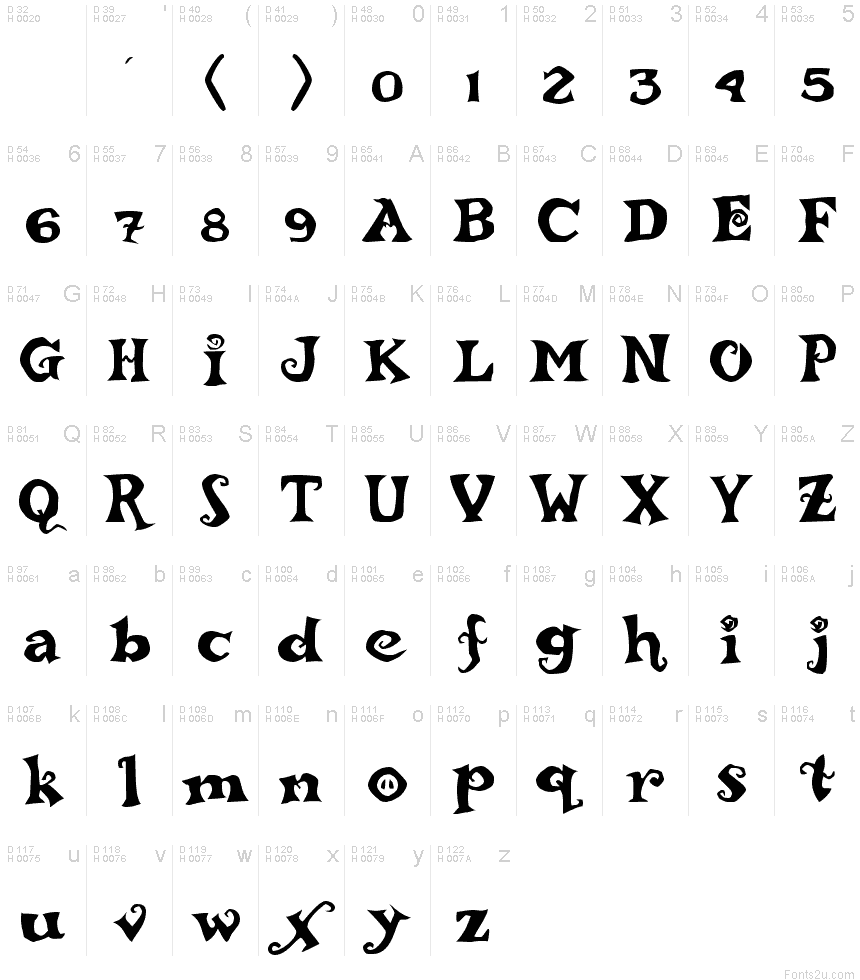
ReBucked od Unauthorized Type to darmowy font display w stylu cartoon z charakterem wyjętym prosto z zadziornej bajki. Litery wyglądają jak narysowane ręcznie i są nieco niepokorne – łączą masywne, czarne kształty z zawiniętymi detalami, ciasnymi łączeniami i nierównymi kątami, co nadaje alfabetowi skoczny, zabawny rytm.
Świetnie sprawdzi się w nagłówkach plakatów, na okładkach książek dla dzieci, nietypowych opakowaniach, kartach tytułowych gier i ulotkach eventowych, gdzie darmowy font ma nieść komiksowy, nieszablonowy przekaz, nie stając się przy tym zbyt wygładzonym. Ponieważ formy liter lekko się kołyszą i wyginają, zamiast trzymać się sztywnych linii, krój ten doskonale nadaje się też do krótkich logotypów, monogramów i dużych napisów, które potrzebują ruchu, a nie porządku.